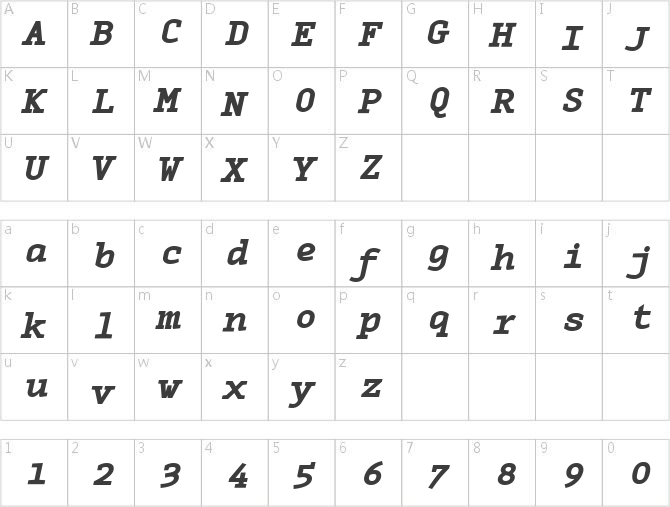
MonoxSerifExtraBoldItalic 詳情頁
MonoxSerifExtraBoldItalic字體字庫是一款讓人賞心悅目、百看不厭的英文字體,適合各類廣告和產(chǎn)品包裝設(shè)計應(yīng)用,字體大小0.04MB,格式為ttf字體,上傳用戶是82年的拉菲,作者/版權(quán)方為未知